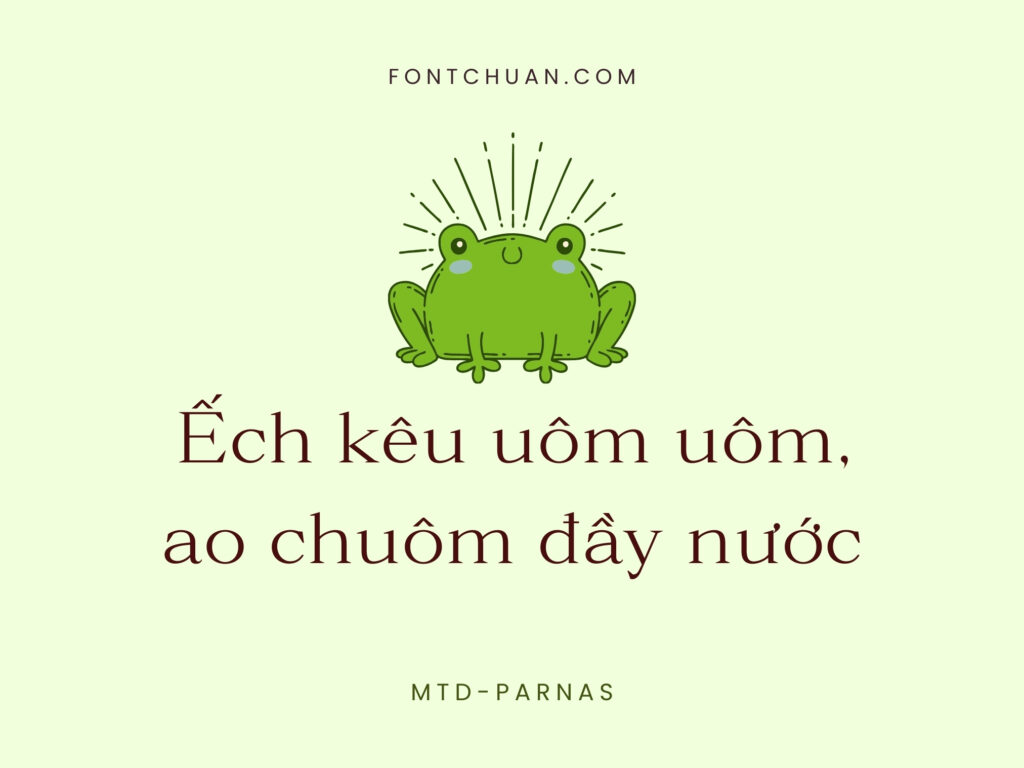
Font MTD Mtd Parnas Việt Hóa
Tác giả Font: Larin Type Co
Font MTD Parnas là một phông chữ serif tuyệt đẹp, được thiết kế bởi Larin Type Co. và phát hành trên Creative Market. Font này đã được Việt hóa bởi Mộc Hạ, hỗ trợ tiếng Việt và hơn 90 ngôn ngữ khác, giúp mở rộng khả năng ứng dụng trong các thiết kế đa ngôn ngữ. Đây là một trong những phông chữ được cộng đồng thiết kế đánh giá cao và ứng dụng trong nhiều dự án sáng tạo, đáp ứng nhu cầu đa dạng của người dùng.
MTD Parnas nổi bật với khả năng sử dụng linh hoạt, có thể thể hiện phong cách cổ điển hoặc biểu cảm và thanh lịch hơn với các ký tự thay thế và ligature độc đáo. Font rất phù hợp cho các thiết kế logo, tiêu đề, bao bì sản phẩm, thiệp mời và các ấn phẩm đòi hỏi sự tinh tế và nghệ thuật. Các ngành nghề phù hợp bao gồm quảng cáo, giáo dục, công nghệ, thiệp cưới và ảnh cưới. Font này cũng lý tưởng cho các sự kiện như Tết, Giáng sinh, Valentine và các lễ hội khác.